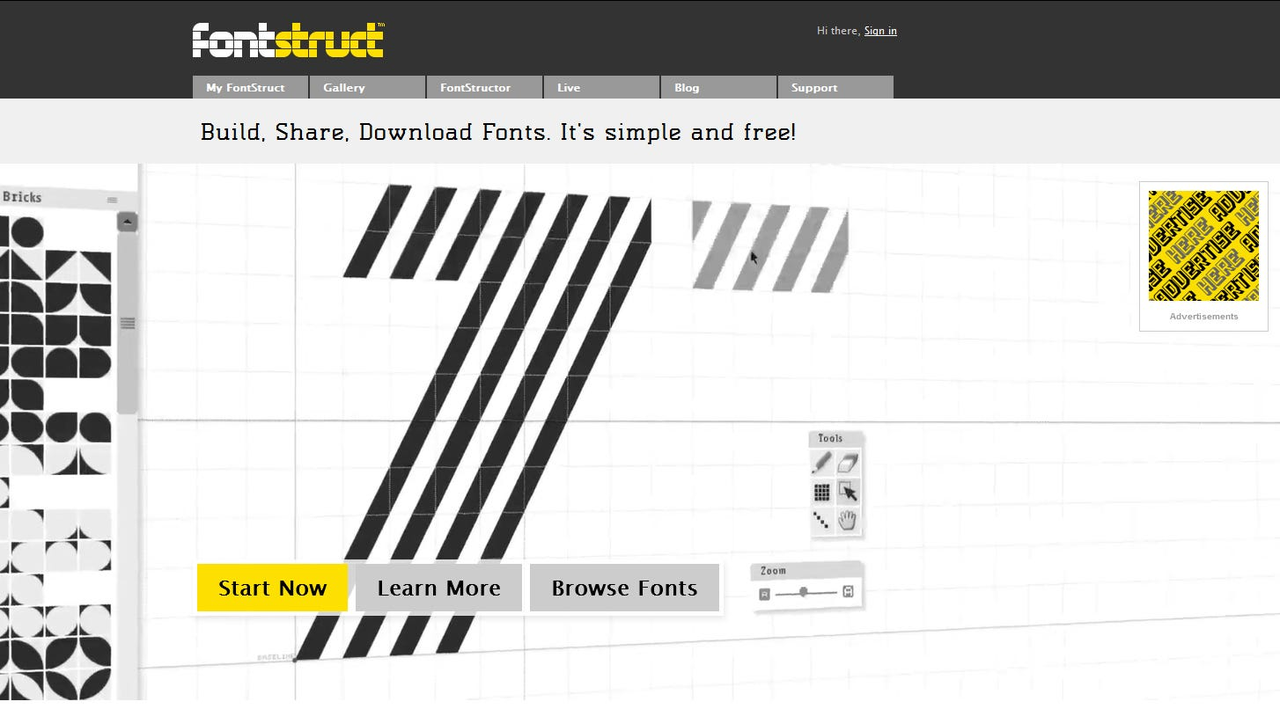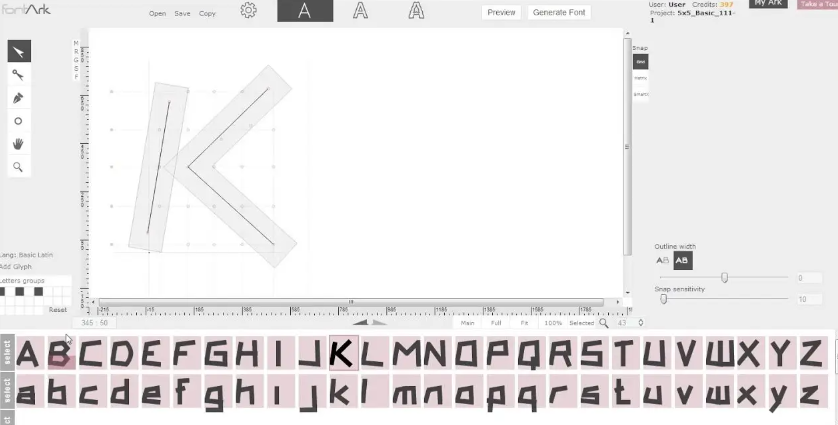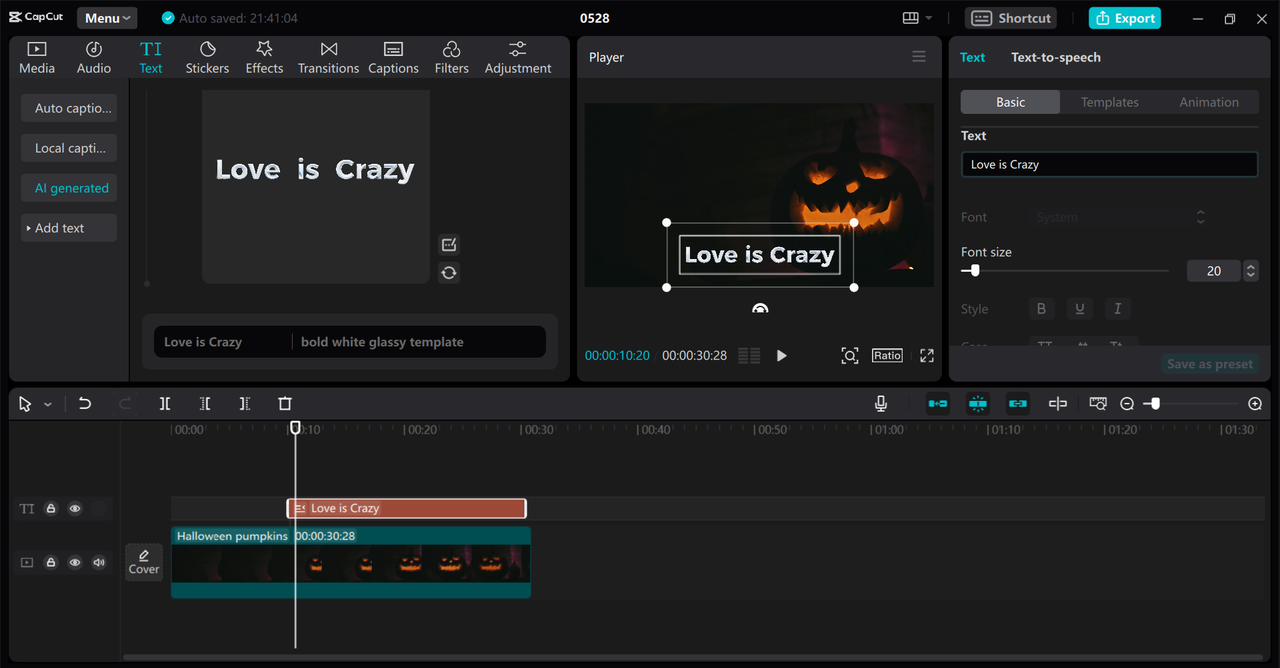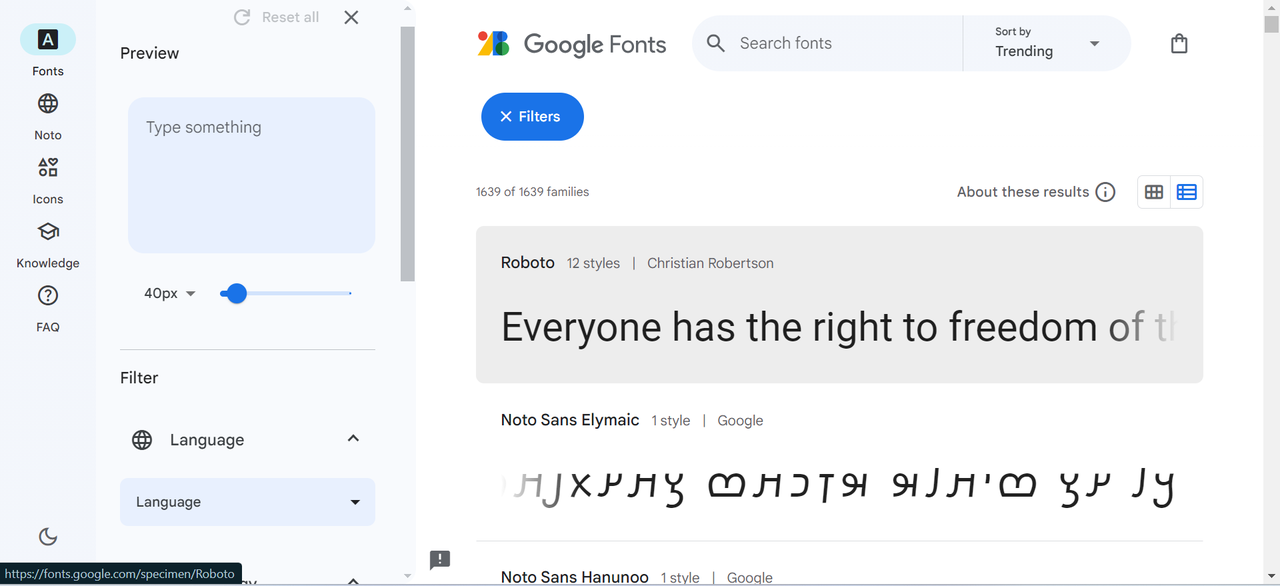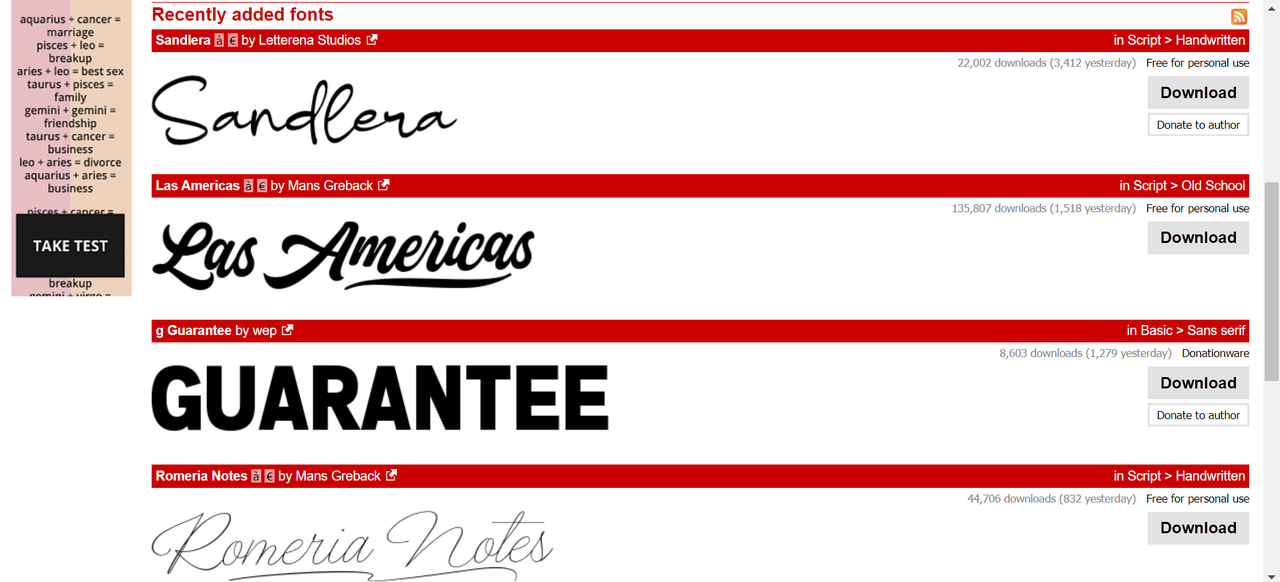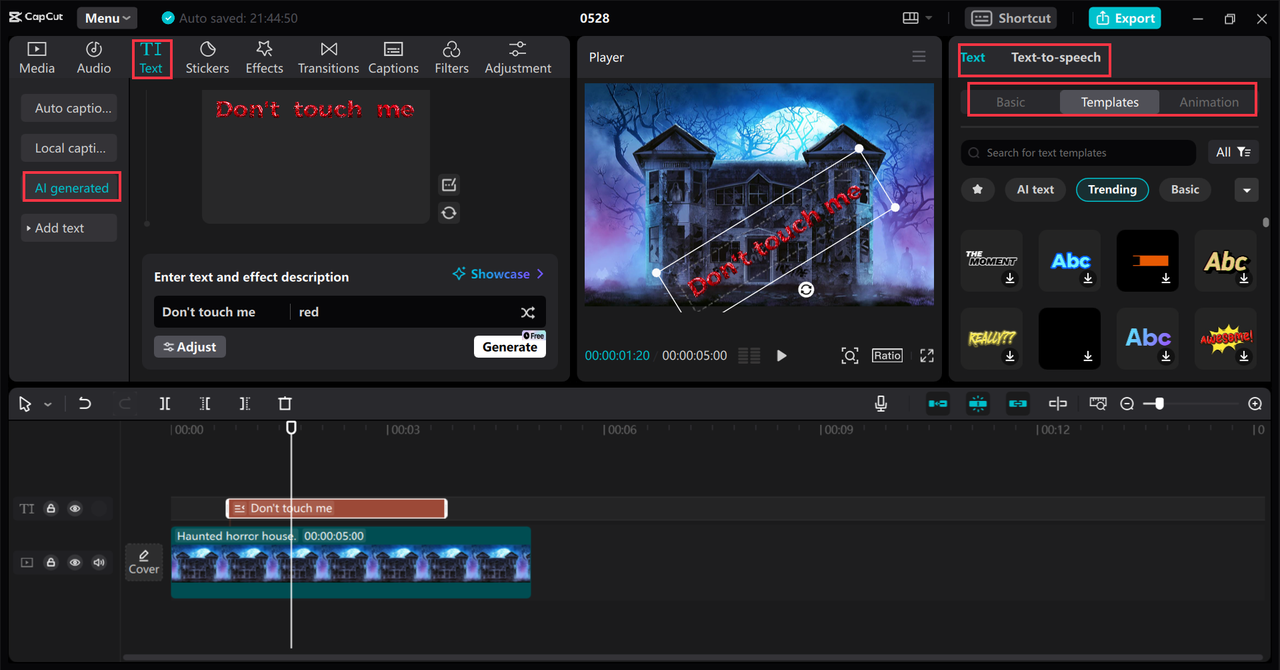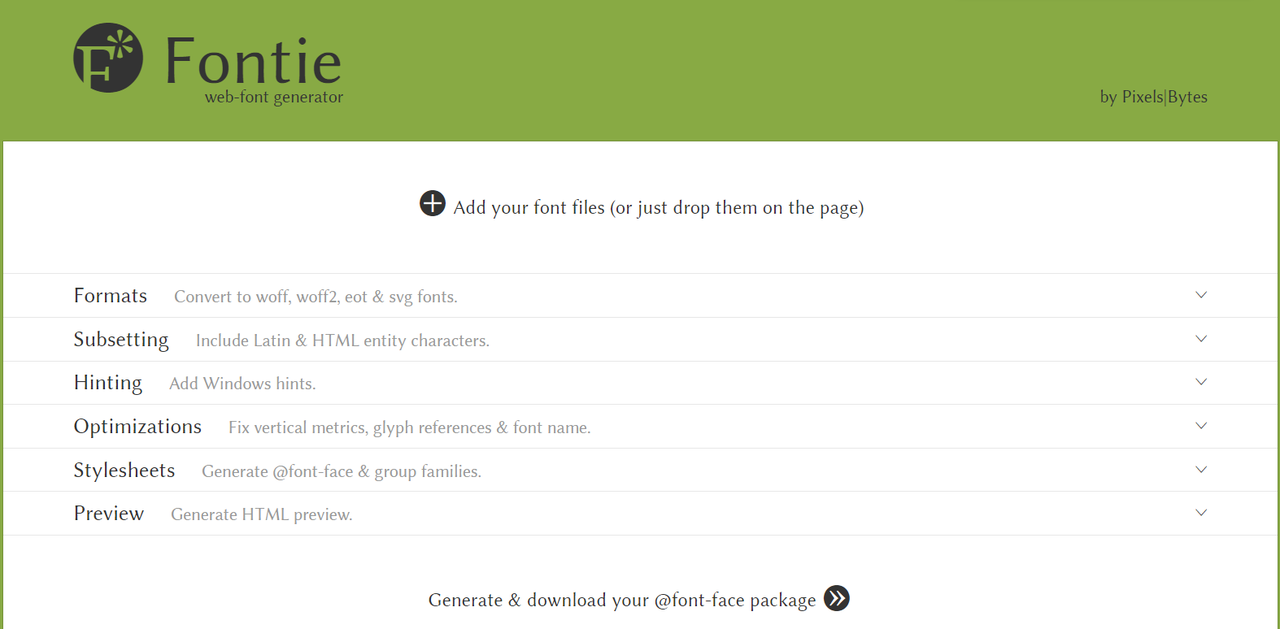
Top 5 instrumente gratuite pentru a face fonturi și litere cool
Fii creativ și fă o impresie de durată cu fontul și literele de top. Explorează o varietate de stiluri la modă și artistice pentru a oferi proiectelor tale video un aspect captivant cu CapCut.
În zilele noastre, atragerea atenției spectatorilor cu imagini atrăgătoare este mai importantă ca niciodată. Fonturile și literele interesante pot face ca conținutul dvs. să iasă în evidență prin adăugarea de elemente de text unice și elegante desenelor dvs. Aceste fonturi pot îmbunătăți aspectul postărilor, biografiilor, profilurilor și videoclipurilor dvs. Cu toate acestea, este crucial să știți cum să alegeți literele de font potrivite pentru proiectul dvs.
În acest ghid, ne vom scufunda în tot ce trebuie să știți despre fonturi și litere interesante și vă vom arăta cum să le utilizați în mod eficient în proiectele dvs.
Cum să alegeți fonturile și literele potrivite
• Definiți tema sau scopul proiectului
Identificarea temei sau scopului proiectului dvs. este primul pas în selectarea fontului perfect. Indiferent dacă proiectul dvs. este distractiv și capricios sau serios și profesional, alegerea fontului dvs. ar trebui să reflecte acel ton. Prin alinierea fontului la tema proiectului dvs., creați o experiență vizuală coezivă și captivantă.
• Luați în considerare lizibilitatea
Deși este tentant să alegeți fonturi elaborate, lizibilitatea ar trebui să fie întotdeauna pe primul loc. Deci, asigurați-vă că publicul dvs. poate citi cu ușurință textul, chiar și în dimensiuni mai mici sau de la distanță. Echilibrarea stilului cu lizibilitatea asigură comunicarea eficientă a mesajului dvs.
• Potriviți fontul cu marca sau mesajul
Alegerea fontului dvs. ar trebui să rezoneze cu identitatea mărcii dvs. și cu mesajul pe care doriți să îl transmiteți. De exemplu, un brand de tehnologie ar putea opta pentru un font elegant și modern, în timp ce un brand pentru copii ar putea prefera un font jucăuș și distractiv. Coerența în selectarea fonturilor întărește recunoașterea mărcii și creează încredere în publicul dvs.
• Testați diferite fonturi
Experimentarea cu diferite fonturi vă permite să vedeți care dintre ele se potrivesc cel mai bine proiectului dvs. Utilizați machete sau modele de eșantioane pentru a vizualiza modul în care diferite fonturi influențează aspectul general. Acest proces vă ajută să luați o decizie în cunoștință de cauză și să găsiți cel mai atrăgător și cel mai potrivit font.
• Luați în considerare asocierea fonturilor
Utilizarea a două fonturi complementare poate adăuga profunzime și interes designului dvs. De obicei, asocierea unui font îndrăzneț și distinctiv pentru titluri cu un font curat și simplu pentru textul corpului creează un aspect echilibrat și profesional. Această asociere eficientă a fonturilor îmbunătățește ierarhia vizuală și ghidează atenția cititorului.
5 instrumente gratuite pentru a crea fonturi și litere grozave
Când selectați litera de font potrivită, trebuie să alegeți generatorul de fonturi care vă oferă rezultatul exact pe care îl doriți. Cu mai multe generatoare de fonturi disponibile pe piață, oamenii se confundă adesea cu privire la ceea ce este cel mai bun pentru proiectul lor. Pentru a vă ajuta, am enumerat 5 instrumente gratuite pentru a crea litere de font unice și elegante.
1. Fonturi Google
Google Fonts este o platformă online cuprinzătoare care oferă o vastă bibliotecă de fonturi open-source gratuite atât pentru proiecte personale, cât și pentru proiecte comerciale. Oferă o interfață intuitivă, ceea ce face ca utilizatorii să poată naviga și previzualiza fonturi în diferite dimensiuni și stiluri. Google Fonts acceptă, de asemenea, integrarea lină cu instrumentele de design web prin intermediul codului HTML și CSS ușor de încorporat, permițând implementarea rapidă și eficientă a fonturilor alese.
Pros
• Biblioteca extinsă de fonturi gratuite.
• Integrare ușoară cu instrumentele de design web.
• Interfață ușor de utilizat.
• Actualizat periodic cu fonturi noi.
Cons
• Opțiuni de personalizare limitate.
• Necesită o conexiune la internet pentru funcționalitate completă.
Google Fonts interface showcasing various font styles
2. Fontie
Fontie este un instrument de conversie a fonturilor online care permite utilizatorilor să convertească orice font în formate web-friendly, cum ar fi WOFF, WOFF2, EOT și TTF. Oferă o gamă largă de opțiuni de personalizare, inclusiv subsetare, sugestie și compresie, pentru a se asigura că fonturile sunt optimizate pentru utilizarea web. Fontie este deosebit de util pentru designerii care doresc să mențină stilul unic al fonturilor lor, asigurându-se în același timp că sunt compatibile și eficiente pentru aplicațiile web.
1. Cum pot face scrieri de stil cool online?
Pentru a crea scrieri în stil cool online, puteți utiliza site-uri web precum Canva, FontMeme sau Generator de text elegant, care oferă diverse fonturi și instrumente de proiectare. Aceste platforme oferă interfețe ușor de utilizat pentru a crea text atrăgător din punct de vedere vizual. Când lucrați la videoclipuri promoționale, puteți utiliza editorul video CapCut desktop pentru a adăuga efecte de text de înaltă calitate.